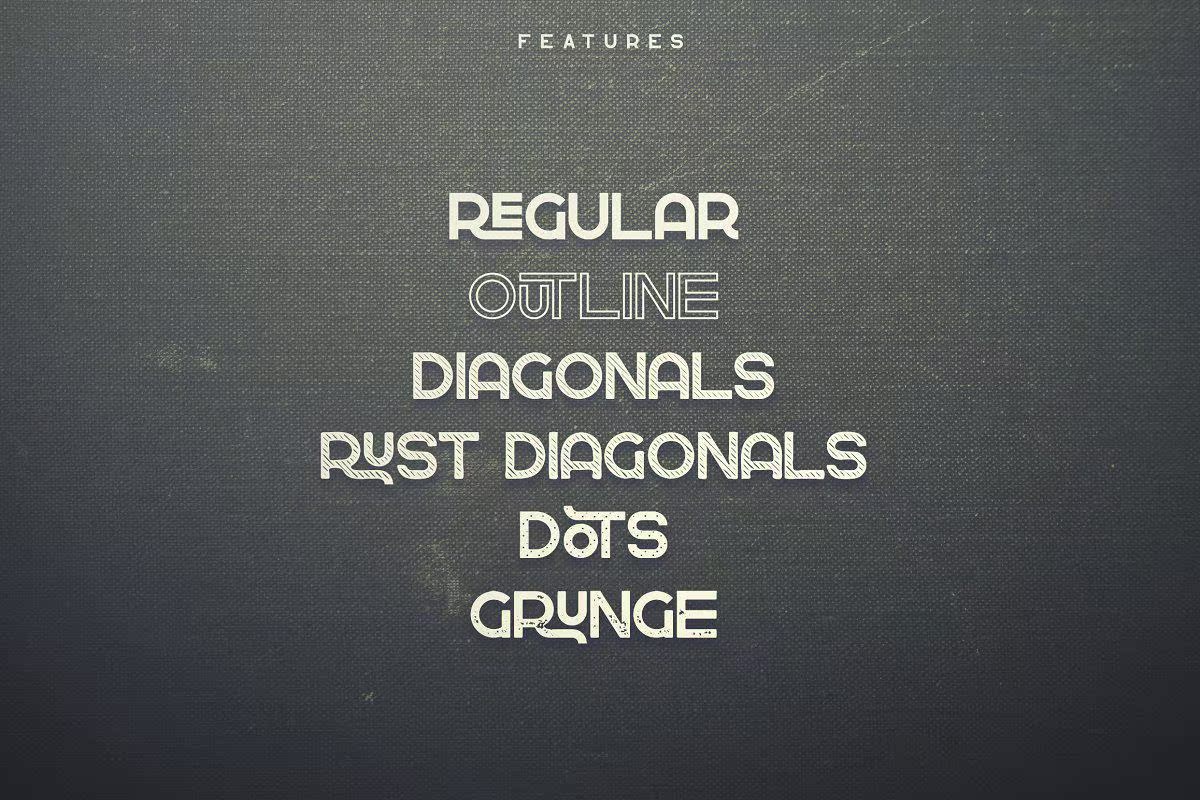
Free Demogreen Display Typeface是一款出色的Vintage Bold Typeface字体。它适用于您的项目,包括徽标、杂志、横幅、包装等。此字体具有多语言特性,您也可以在您的语言中使用。此外,它还具有特殊的字形和连字,以专业方式查看您的项目。因此,此免费版本仅适用于个人使用许可证,但请不要担心,您可以购买此版本的更多功能。